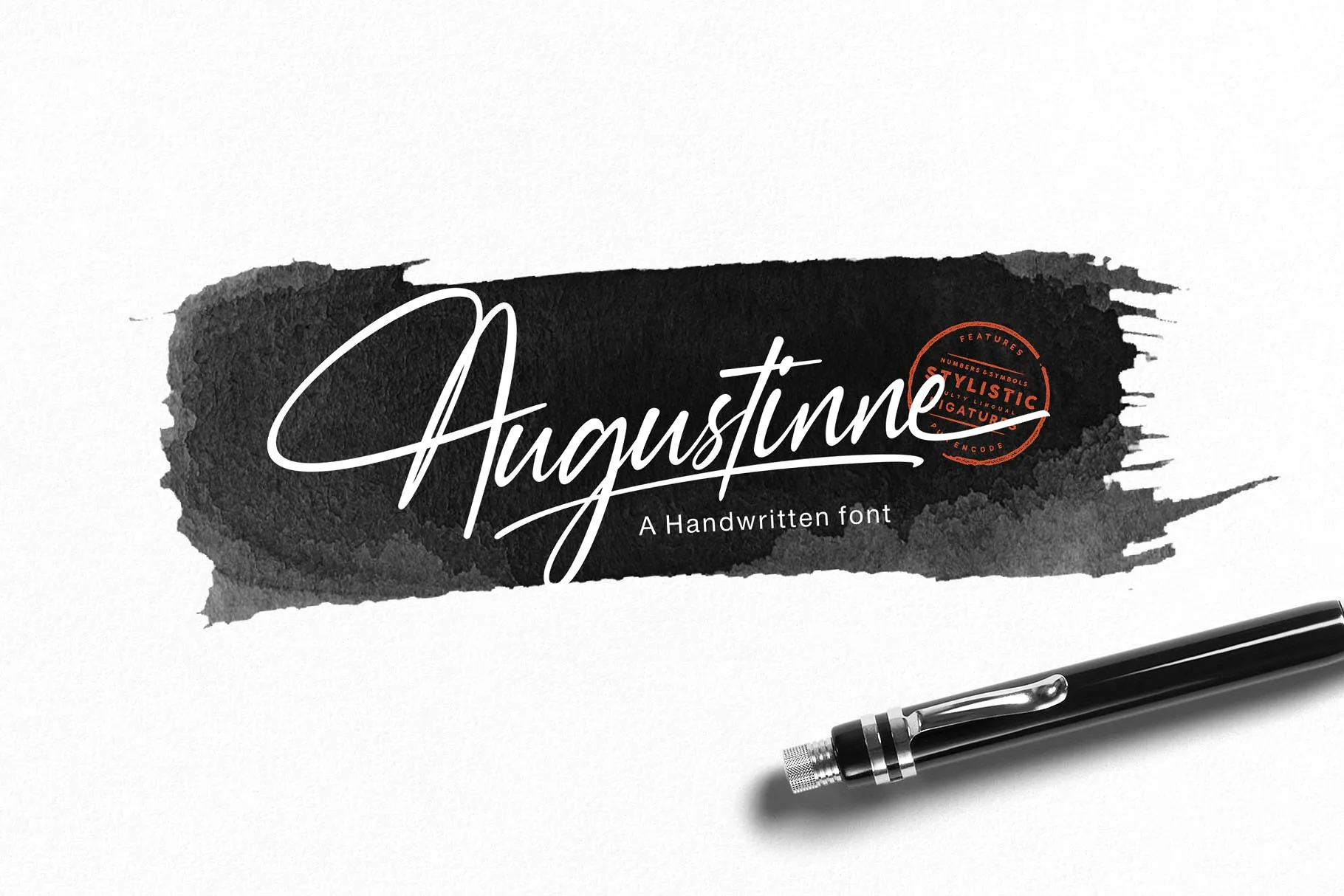
Augustinne Handwritten Font – Fonte Grátis
Augustinne Handwritten Font
Esta é uma fonte autêntica para escrita à mão que você pode usar para alcançar um sentimento de letra escrita a mão. Ela se adequa perfeitamente às necessidades modernas do design gráfico, sendo ideal para cartões, citações impressas, logotipos, assinaturas, embalagens de produtos, capas de livros, convites, escritas em molduras e cabeçalhos, além de qualquer coisa que sua imaginação possa criar. Esta font é espaçosa e confortável, proporcionando uma sensação tranquila e versátil. Augustinne garante que seus textos se destacam, tornando-a perfeita para cartões, citações impressas, logotipos, assinaturas, embalagens de produtos, capas de livros, convites, escritas em molduras e cabeçalhos, além de qualquer coisa que sua imaginação possa criar. Em resumo, Augustinne é uma fonte ideal para o seu design gráfico moderno, garantindo um destaque impecável para seus projetos.